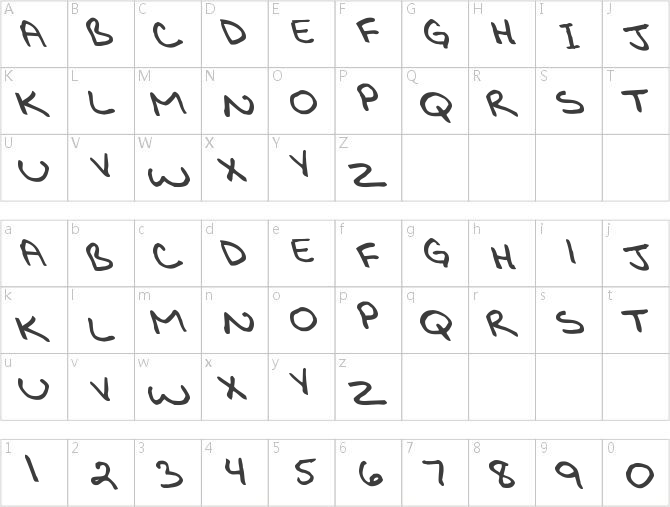
Bikly Bold Extreme Lefty Font 詳情頁
Bikly Bold Extreme Lefty Font字體字庫是一款讓人賞心悅目、百看不厭的英文字體,適合各類廣告和產(chǎn)品包裝設(shè)計應(yīng)用,字體大小0.08MB,格式為ttf字體,上傳用戶是W^xzj,作者/版權(quán)方為未知